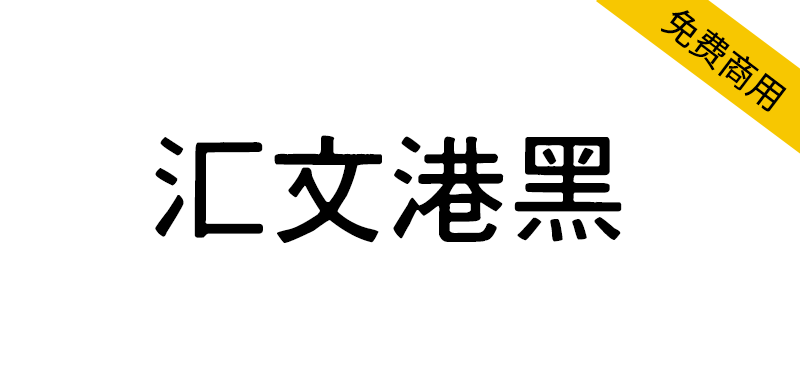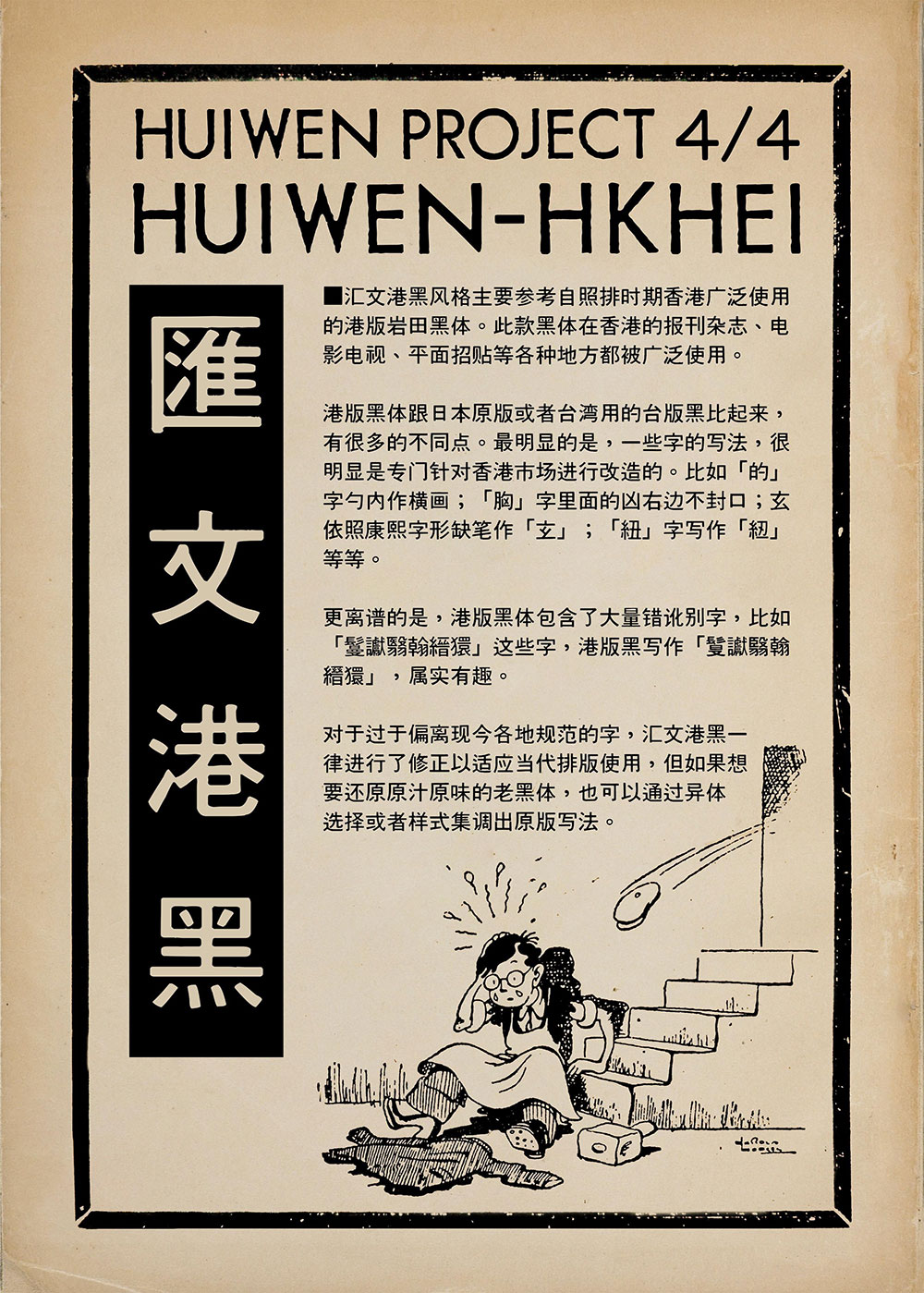
【汇文港黑】一款复古印刷效果的黑体字体
想给设计注入地道港风复古感?这款源自香港照排时代的「汇文港黑」字体,藏着霓虹招牌与旧报刊的视觉密码。它曾因大量错讹别字成为时代烙印,如今设计师既保留了原版异体字供情怀复刻,又贴心修正了现代排版难题。一秒切换新旧两种韵味,让每个字都成为穿梭时光的视觉符号。
【汇文港黑】一款复古印刷效果的黑体字体
汇文港黑风格主要参考自照排时期香港广泛使用的港版岩田黑体。此款黑体在香港的报刊杂志、电影电视、平面招牌等各种地方都被广泛使用。
港版黑体跟日本原版或者台湾用的台版黑比起来,有很多的不同点。最明显的是,一些字的写法,很明显是专门针对香港市场进行改造的。更离谱的是,港版黑体包含了大量错讹别字,
对于过于偏离现今各地规范的字,汇文港黑一律进行了修正以适应当代排版使用,但如果想要还原原汁原味的老黑体,也可以通过异体选择或者样式集调出原版写法。
【汇文港黑】一款复古印刷效果的黑体字体